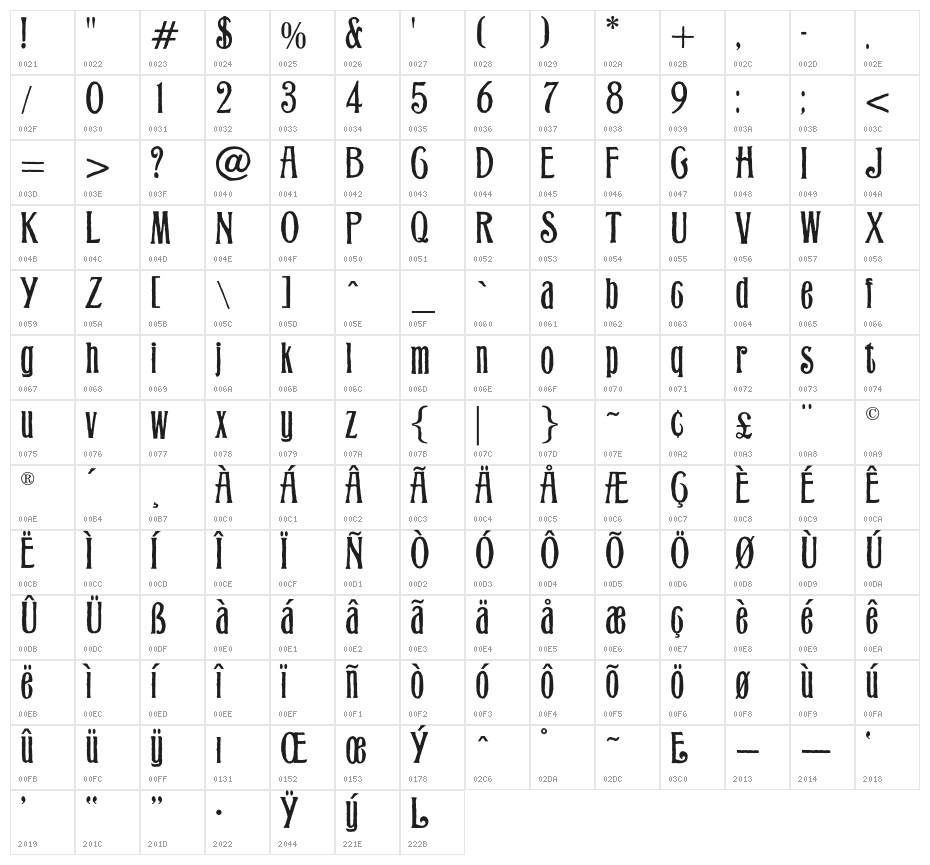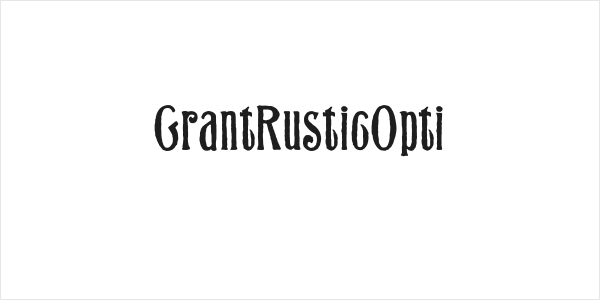
GrantRusticOpti Font
| Категория | Retro |
| Общий стиль | Vintage |
| Рекомендуемые проекты | Ideal for projects that require a personal touch, such as invitations, posters, branding for artisanal products, or any design seeking a vintage or handcrafted look. |